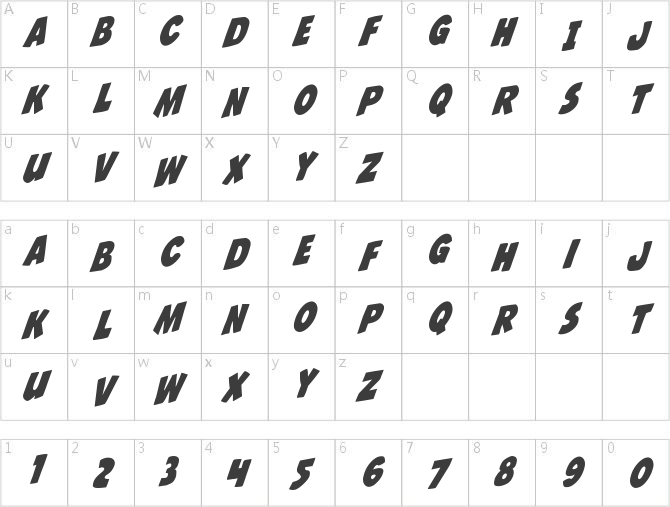
Jack's Candlestick Condensed Ro
Jack's Candlestick Condensed Ro字体字库是一款让人赏心悦目、百看不厌的英文字体,适合各类广告和产品包装设计应用,字体大小0.06MB,格式为ttf字体,上传用户是17199970014,作者/版权方为未知